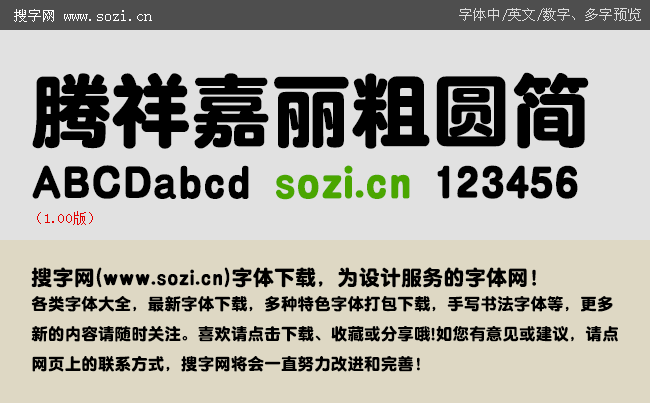
騰祥嘉麗粗圓簡(jiǎn)
搜字網(wǎng)提供一款騰祥嘉麗粗圓簡(jiǎn)字體下載,該字體每個(gè)漢字都經(jīng)過(guò)精心設(shè)計(jì),筆畫(huà)粗細(xì)均勻、結(jié)構(gòu)美觀。每個(gè)字的圓角、圓頭、勾形都極光潔、風(fēng)格統(tǒng)一,字形放大不變形,縮小顯示清晰,適用于樣本畫(huà)冊(cè),報(bào)紙排版,網(wǎng)頁(yè)標(biāo)題等廣告設(shè)計(jì)應(yīng)用。